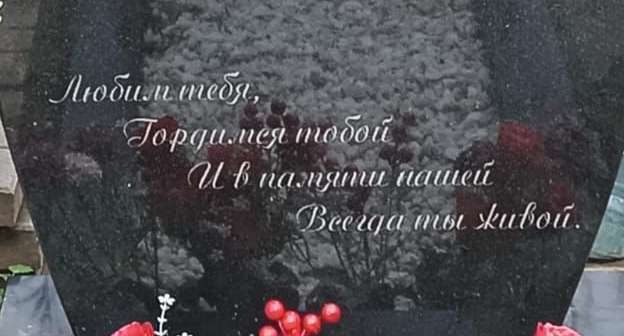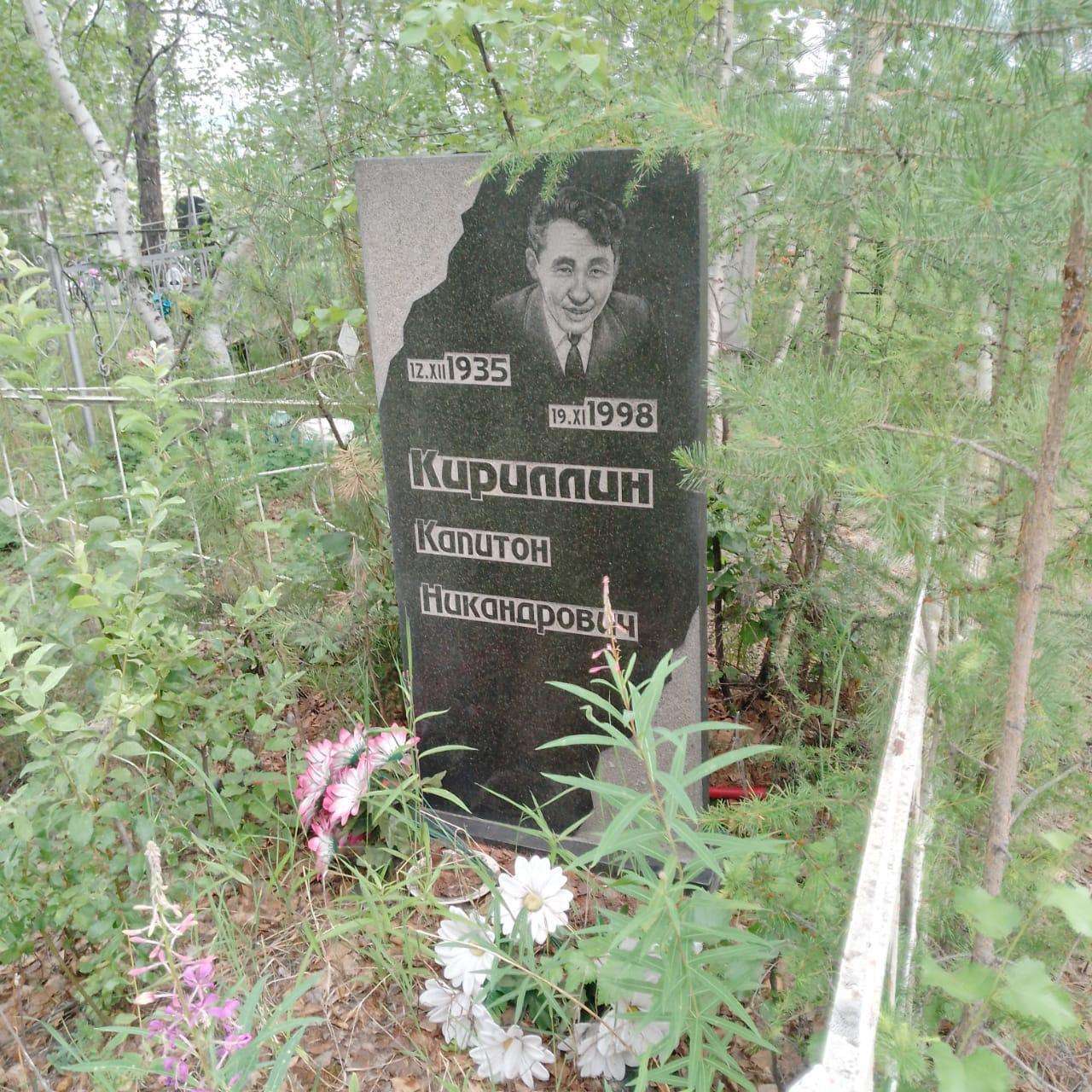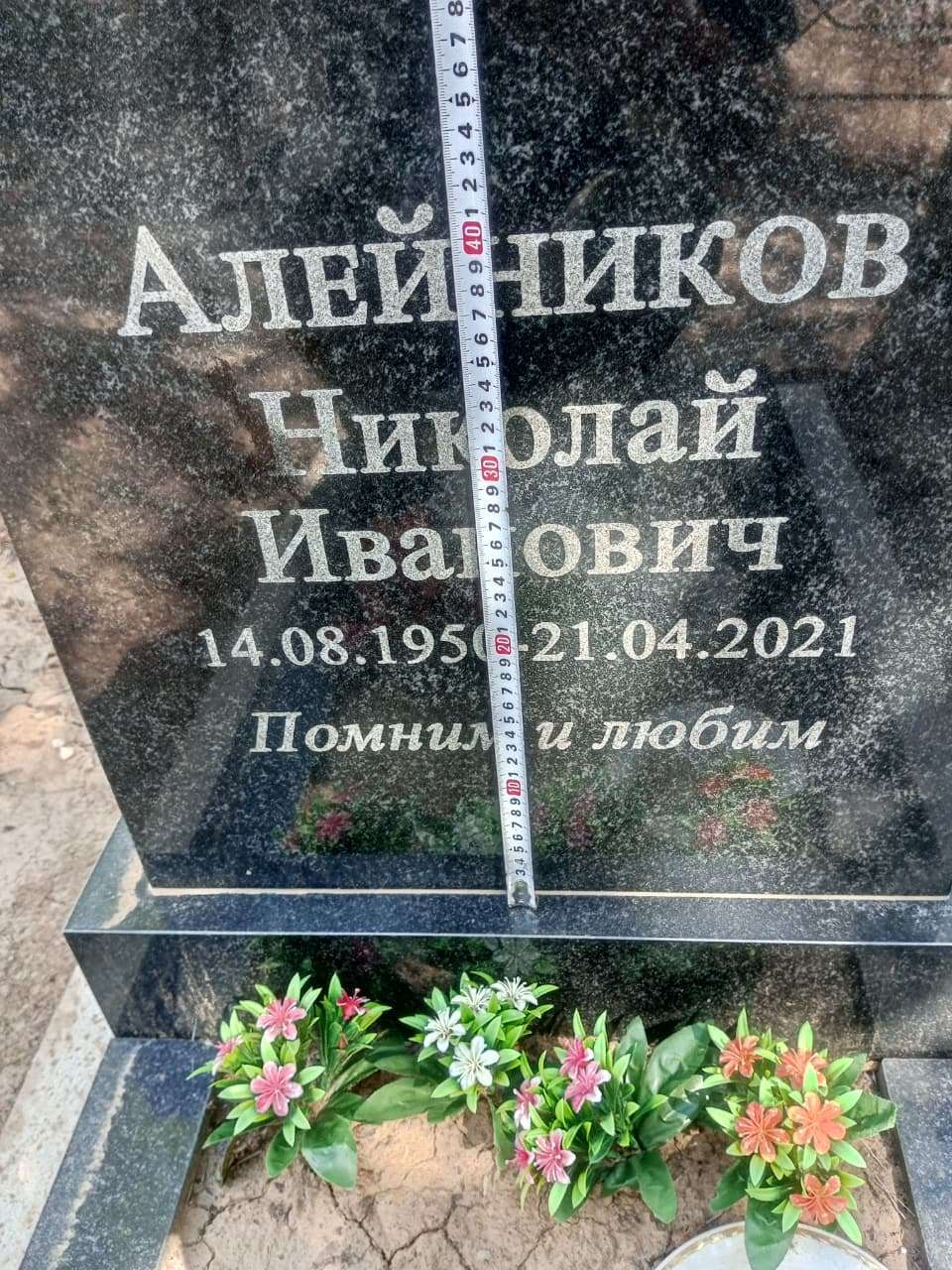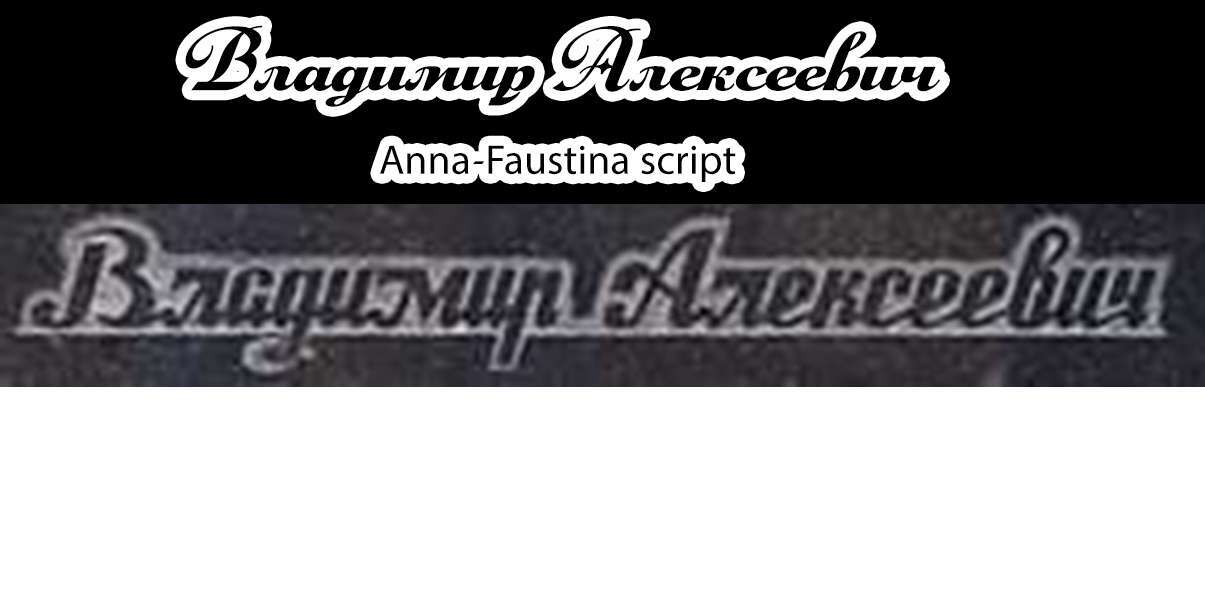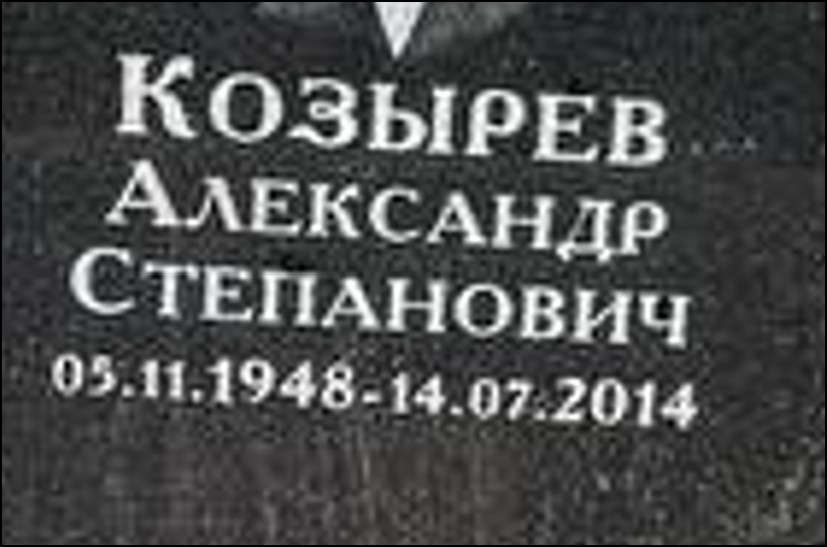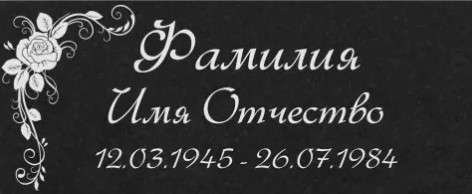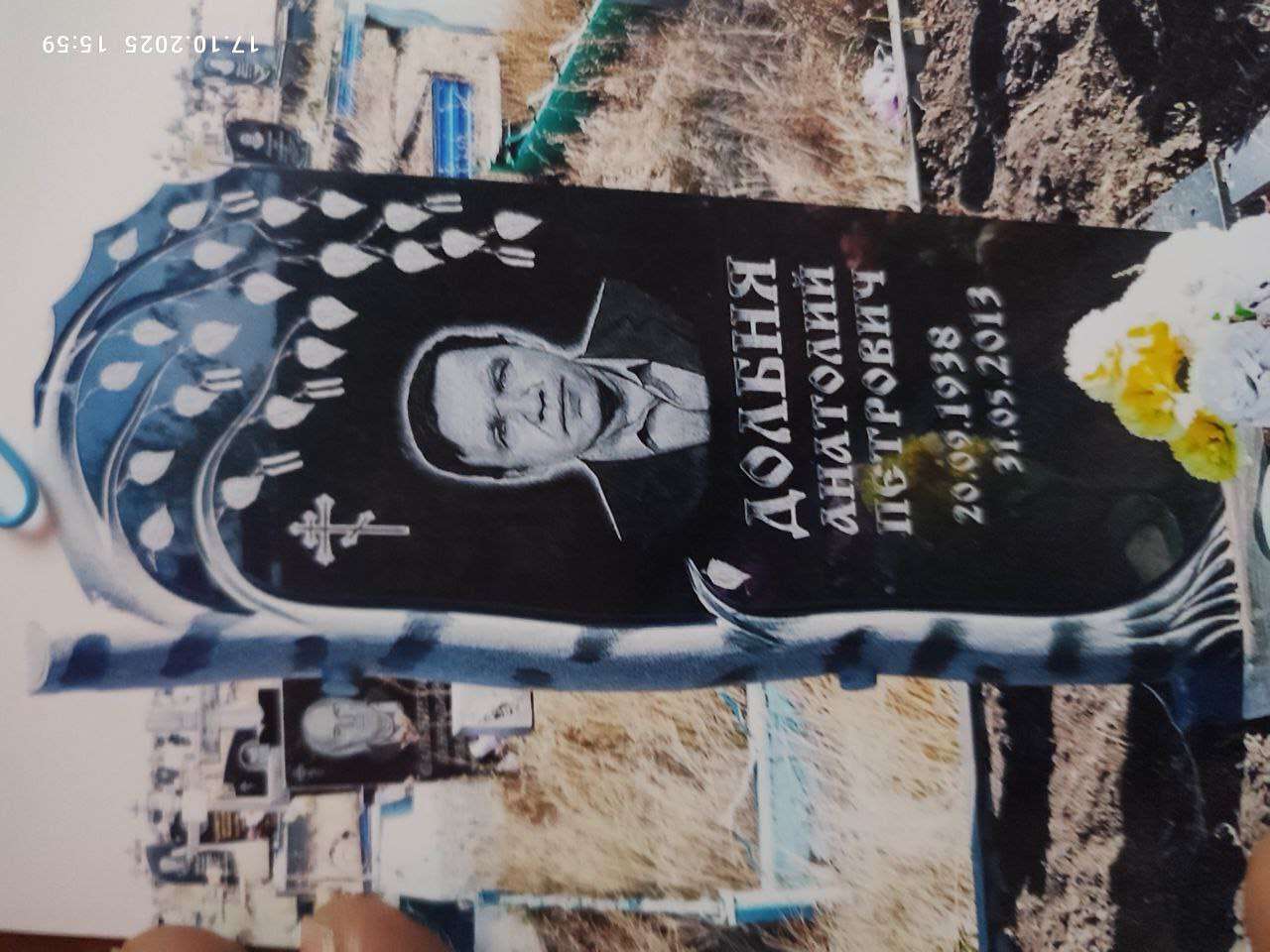
aazt Опубликовано 11 сентября, 2025 товарищи! помогите определить шрифт
Connar Опубликовано 11 сентября, 2025 тут все буквы разные. какой шрифт.......... не видно что ли. 1
Владимир65765187 Опубликовано 22 сентября, 2025 @Storn Очень похож, но нет
Connar Опубликовано 22 сентября, 2025 да он это. просто обычный+жирный в фотошопе сделан. и все буквы заглавные
a-revus Опубликовано 22 сентября, 2025 @Владимир65765187 в Фотошопе слои-стиль слоя-обводка-размер пару пикселей добавь снаружи и будет он 1
Катенька Опубликовано 23 сентября, 2025 Может кто-то знает что это за шрифт? Подскажите пожалуйста
Brtlg Опубликовано 29 сентября, 2025 Нужен опытный дизайнер шрифта, который может восстановить шрифт ручной работы по фотографии для другого памятника. -Только с образцами подобных работ. -
a-revus Опубликовано 29 сентября, 2025 @Brtlg не нужен никакой дизайнер, скотчем лист А-4 на камень крепите и толстым карандашом переносите буквы на бумагу, так получается образец с точным размером буквы. В корэл драв образец переводится в кривые. Если какой либо буквы нет, то она допридумывается на основании образца.
a-revus Опубликовано 29 сентября, 2025 @Brtlg а я вам о чём? Делайте шаблон, сканируйте в разрешении 300dpi чтоб размер 1х1 был, и этот файл откликнувшемуся отправляйте. Любой гравер эту работу ежедневно делает, или вы считаете , что мы к дизайнерам обращаемся, чтоб добивку на участке сделать?
perez Опубликовано 1 октября, 2025 люди подскажите шрифт, "З" как Elizabeth, а "Р" хз какой
Art_em Опубликовано 11 октября, 2025 Подскажите подходящий шрифт. Выполнено ручником.
igors Опубликовано 11 октября, 2025 (изменено) @Art_em видел еще подобные но и там все буквы разные Изменено 11 октября, 2025 пользователем igors 2
Нимфа Опубликовано 13 октября, 2025 Здравствуйте, если у кого есть такой шрифт поделитесь пожалуйста, спасибо.
Art_em Опубликовано 13 октября, 2025 @Нимфа Это шрифт Таймс и эффекты слоя: https://disk.yandex.ru/d/iDZE8G3behdcYg 2
Ivawan2 Опубликовано 15 октября, 2025 Приветствую! Подскажите шрифты, если есть такие, пожалуйста <3
Stan Опубликовано 28 октября, 2025 Добрый день. Помогите пожалуйста определить шрифт